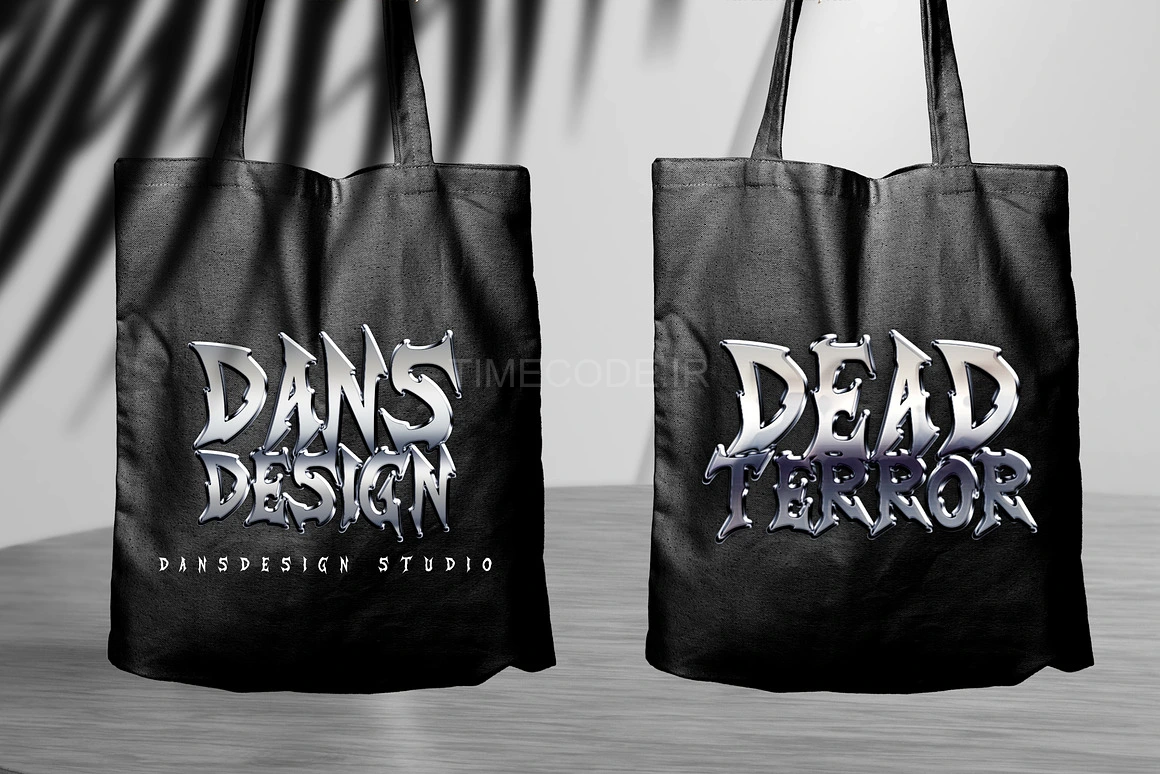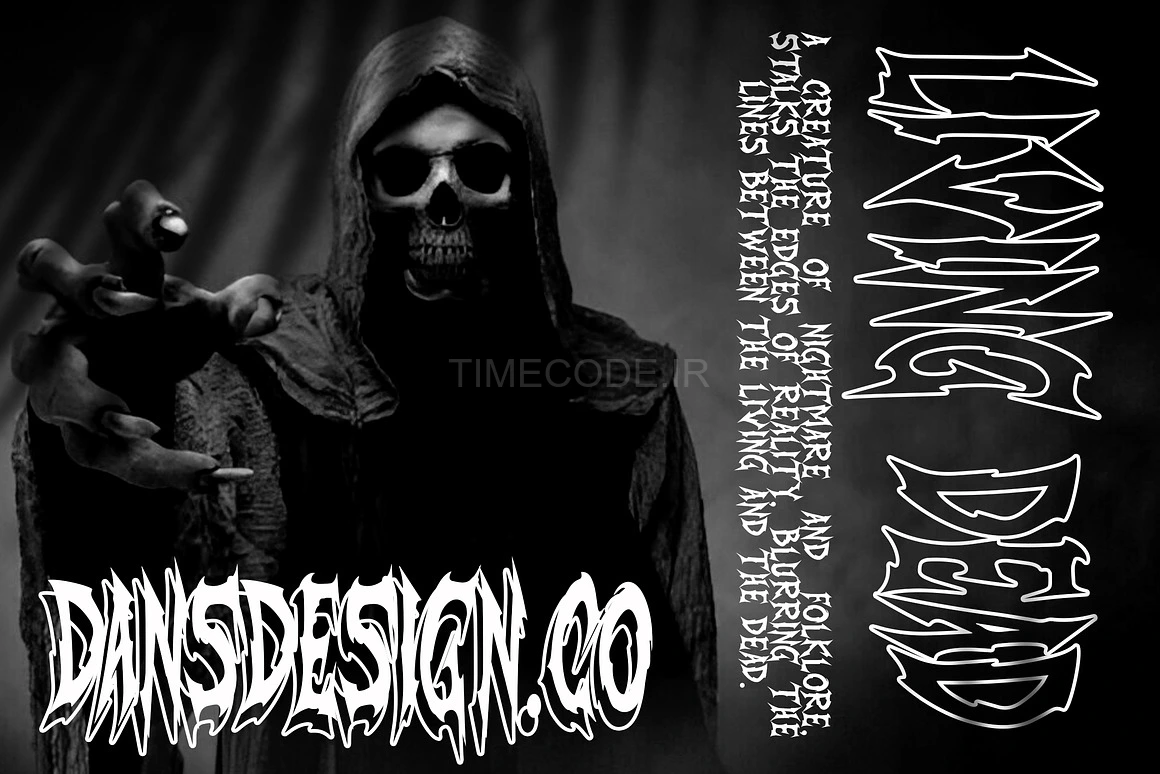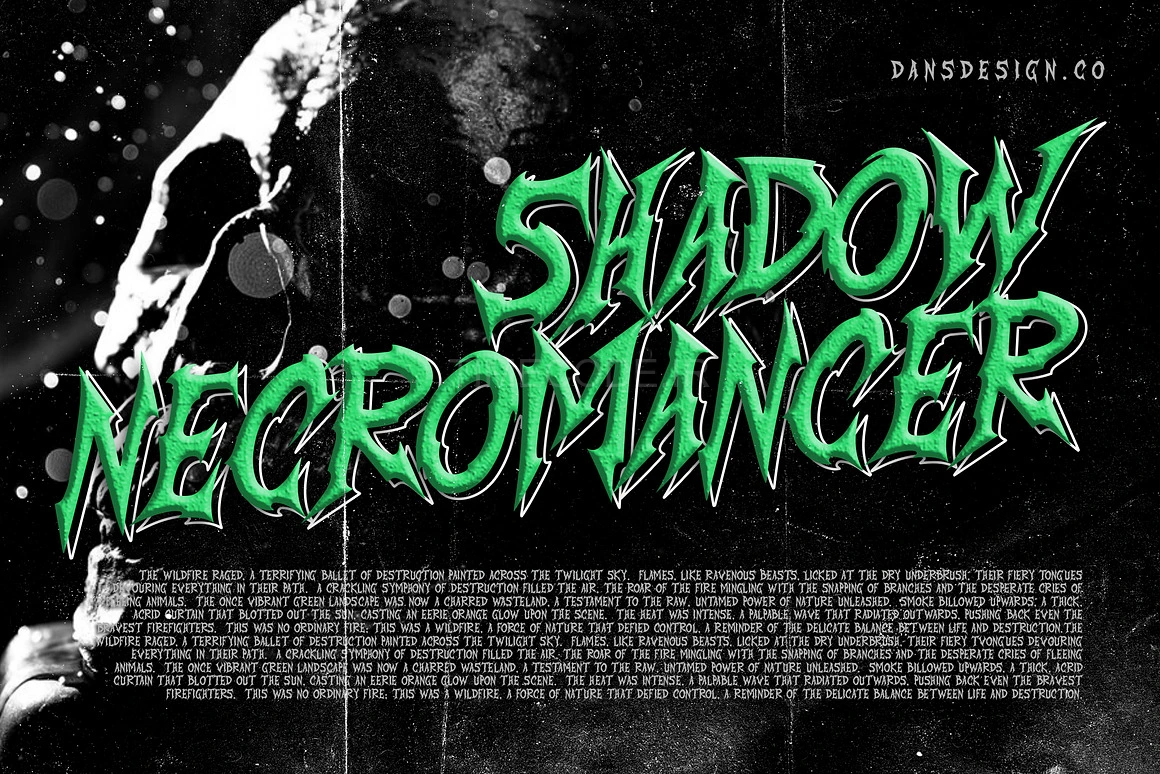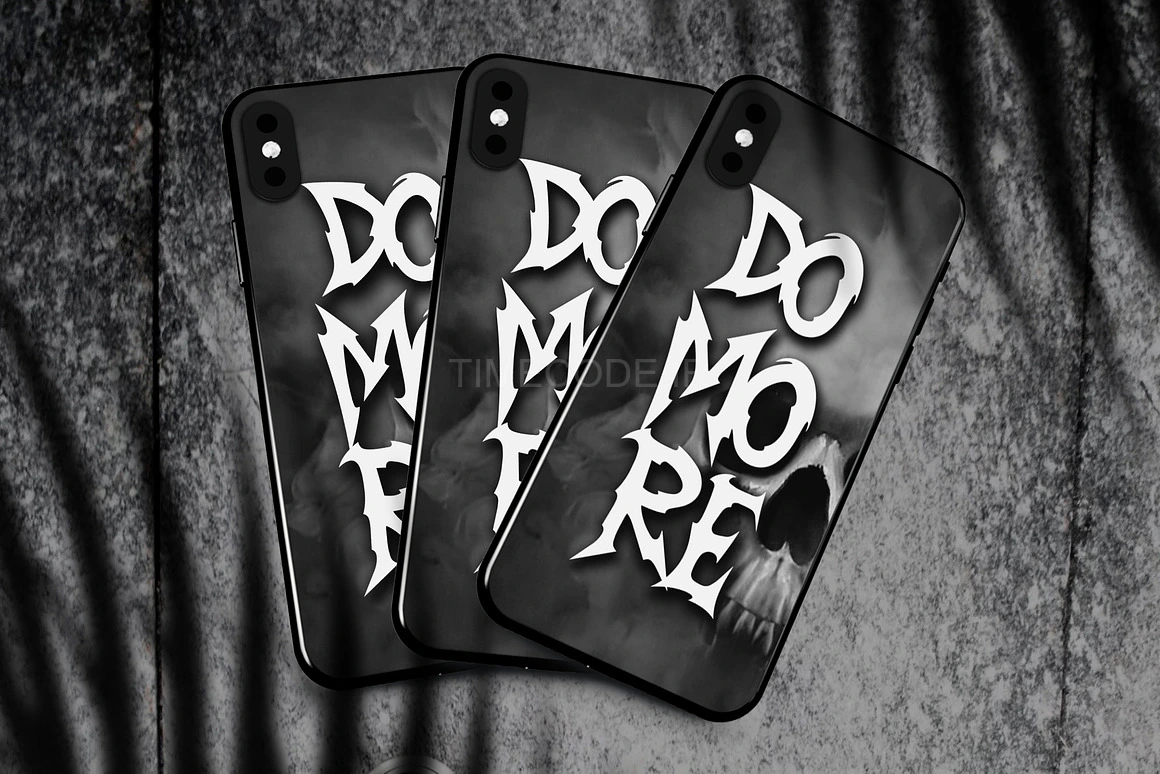
• Novocane – Horror Metal Display Font
Novocane یک فونت نمایشی متال-ترسناک و بسیار برجسته است که برای تاریکی ساخته شده. این تایپ‌فیس با لبه‌های تیز، انحناهای شوم و طراحی با کنتراست بالا، ترس و آشوب خالص را به نمایش می‌گذارد و برای عناوین فیلم‌های ترسناک، پوسترهای اسلشر، محصولات هالووین و داستان‌پردازی بصری خشن، عالی است.
Novocane با الهام از حروف‌نویسی سبک هوی متال و مجلات ترسناک زیرزمینی، نگرشی مرگبار به هر کلمه می‌بخشد. هر کاراکتر مانند یک سلاح شکل گرفته و تداعی‌گر خون، استخوان و طغیان است. این فقط یک فونت نیست، بلکه یک فریاد بصری است.
ویژگی‌های کلیدی:
• کاراکترهای دفرمه و الهام‌گرفته از ژانر وحشت با زوایای تیز
• استایلی کشنده برای طرح‌های اسلشر، مردگان متحرک، علوم غریبه و خونین
• شامل حروف بزرگ، کوچک، اعداد و تمام علائم نگارشی
عالی برای:
• پوسترها و تریلرهای فیلم‌های ترسناک
• دعوت‌نامه‌ها و محصولات مهمانی هالووین
• لوگوها و کاور آلبوم‌های گروه‌های متال
• برندینگ و تابلوهای خانه‌های تسخیرشده
• جلدهای کتاب ترسناک، مجلات و محتوای فانتزی تاریک
جرات کنید سکوت را بر هم بزنید—Novocane برای فریادها، سایه‌ها و هر آنچه در تاریکی کمین کرده، ساخته شده است. طرح‌های ترسناک شما دیگر هرگز مثل قبل نخواهند بود.
Novocane – Horror Metal Display Font with Sharp Shape
Novocane is a terrifyingly bold horror metal display font forged for darkness. With razor-sharp edges, sinister curves, and high-contrast design, this typeface drips with raw fear and chaos—perfect for horror movie titles, slasher posters, Halloween merch, and extreme visual storytelling.
Inspired by heavy metal lettering and underground horror zines, Novocane brings a deadly attitude to every word. Each character is shaped like a weapon, evoking blood, bone, and rebellion. It's not just a font—it’s a visual scream.
Key Features:
Distorted, horror-inspired characters with sharp angles
Killer style for slasher, undead, occult, and gore designs
Uppercase, lowercase, numbers, and full punctuation
Perfect for:
Horror movie posters and trailers
Halloween party invites and merchandise
Metal band logos and album covers
Haunted house branding and signage
Creepy book covers, zines, and dark fantasy content
Dare to disturb the silence—Novocane is made for screams, shadows, and everything that lurks in the dark. Your horror designs will never be the same.